طراحی لوگو (نشانه) سایت پرشین لوگوتایپ
سایت پرشین لوگوتایپ Persian Logotype به طور تخصصی در زمینه طراحی نشانه (لوگو) و نشانه نوشته (لوگوتایپ) فارسی فعالیت می کند. کار با حروف فارسی و طراحی آثاری با تکیه بر هویت و قدرت بی نظیر خط فارسی با رویکردی مبتنی بر کاربرد و نیاز روز خط مشی اصلی این سایت است و ارتقای سطح کیفی نشانه های فارسی و خلق آثار بدیع و زیبا در این زمینه به منظور افزایش وسعت و کیفیت در انتخاب سفارش دهنده را هدف خود قرار داده است.
در طراحی این نشانه که روح فارسی و ایرانی در ابتدا و در نگاه اول در کالبد آن، چشم را نوازش دهد، از المان هایی مرتبط با موضوع فعالیت و ریشه دار در هویت و فرهنگ غنی پارسی استفاده شده است. موارد لحاظ شده در طراحی این نشانه به شرح زیر است:
1-قلم نی
یگانه ابزار ابداع و نگارش خطوط، در هنر خوشنویسی اسلامی(عربی و فارسی) است. هنری غنی، برای بیان مفاهیمی غنی که کشش قلم نی بر کاغذ و صریر موسیقیایی آن، همچنان که بازگوی آنهاست، نوای نی نیز در فرهنگ و ادبیات ما حکایت ها و اسراری دارد. آنجا که جلال الدین محمد بلخی معروف به مولوی می سراید:
…بشنو از نی چون حکایت می کند…
…نی حدیث راه پرخون می کند قصه های عشق مجنون می کند…
…آتش است این بانگ نای و نیست باد هرکه این آتش ندارد نیست باد…
قابل ذکر است که فاق یا شیار، شکافی است که در سر قلم نی(اصطلاحا میان وحشی و انسی) ایجاد می کنند تا مرکب راحت و یکنواخت بر کاغذ منتقل شود. و این مورد نیز در طراحی فرم سر قلم نی لحاظ گردیده است.
2-نقطه
نقطه از سه جهت دارای اهمیت می باشد؛ اول این که نقطه خود از نشانه ها و علائم نگارشی محسوب می شود که در واقع به نوعی زبان و لحن نوشتار را برای درک و دریافت صحیح خواننده شکل می دهند.
دوم این که اولین عنصر بصری در مبانی هنرهای تجسمی نقطه است و باقی عناصر از نقطه و حرکت آن شکل می گیرند.
و سومین و مهم ترین وجه این است که از نقطه در خوشنویسی به عنوان مقیاس و واحد تناسبات حروف، استفاده می کنند یعنی طول و عرض حروف، میزان کشیدگی ها و… با نقطه تعیین می شود، همچنان که رعایت تناسبات و اصول گریدبندی، از شروط لازم برای طراحی نشانه و خصوصا نشانه نوشته می باشد.
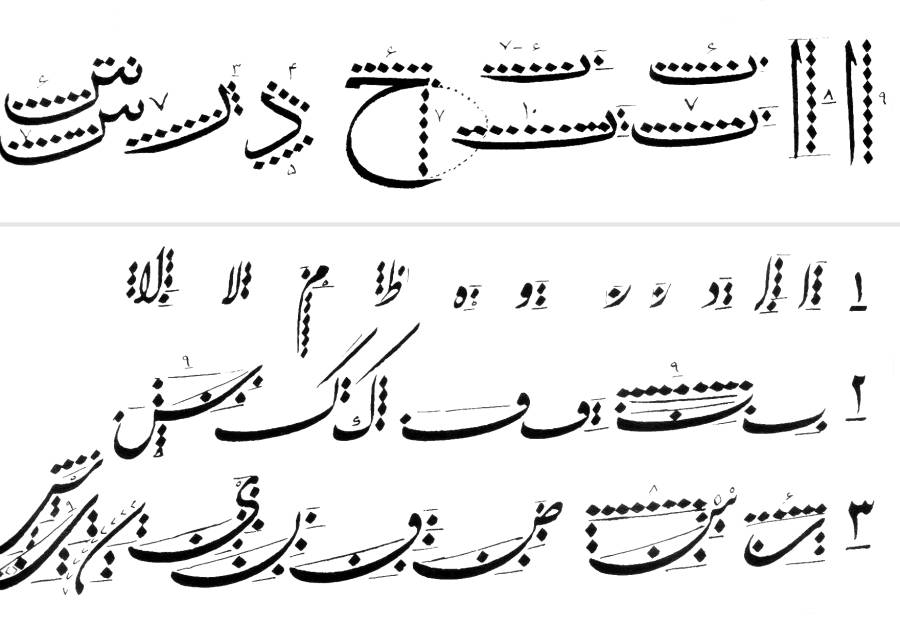
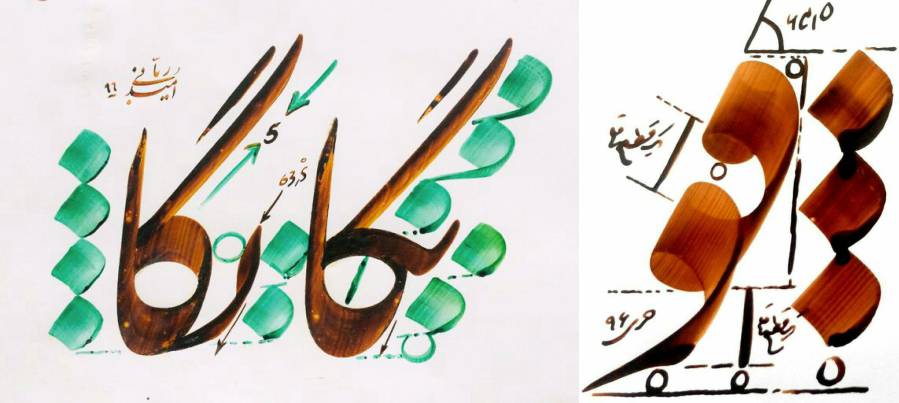
3-خط نستعلیق
خط نستعلیق شناسنامه و نماد هنر ایرانی محسوب شده و به اعتبار تناسب دقیق در دور و سطح آن و نیز به لحاظ جمال شناسی به عروس خطوط اسلامی شهرت دارد. پیوند خط نستعلیق با ادبیات فارسی به گونه ای است که هرگاه واژه ادبیات فارسی شنیده شود، ناخودآگاه تصاویری از خط نستعلیق و آثار ادبی نوشته شده با آن در ذهن متبلور می شود. در طراحی نشانه سایت پرشین لوگوتایپ از نقطه و حرف «واو» خط نستعلیق به صورت مستقیم استفاده شده و حرف «الف» نیز در فرم کلی و خصوصا سرک آن روحیه نستعلیق خود را حفظ کرده است.
4-گل شاه عباسی
استفاده از حرف “واو” نستعلیق و در کنارش حرف “الف” به صورت متعاکس و قرینه، همراه با فرم سر قلم نی، شکل ساده شده ای از گل شاه عباسی را به نمایش گذاشته اند. نقش معروفی که در طرح های فرش، کاشی، تذهیب و دیگر هنرهای اصیل ایرانی بکار رفته و تداعی کننده زیبایی، اصالت و فرهنگ ایرانی است.
5-خط توأمان یا متعاکس
که به نام های مثنی، برگردان و آینه ای(در ترکی) نیز شهرت دارد، از شیوه های تزئینی و تفننی خطاطی بوده است بدین روش که کلمه یا عبارتی را به صورت دوتایی و قرینه هم، در ترکیبی زیبا و چشم نواز، به انواع خطوط کوفی، ثلث، نسخ، نستعلیق، محقق و… می نوشته اند و گاهی هم آن را به هیئت اشکال هندسی، گیاهان و یا سایر موجودات و اشیاء در می آورده اند.
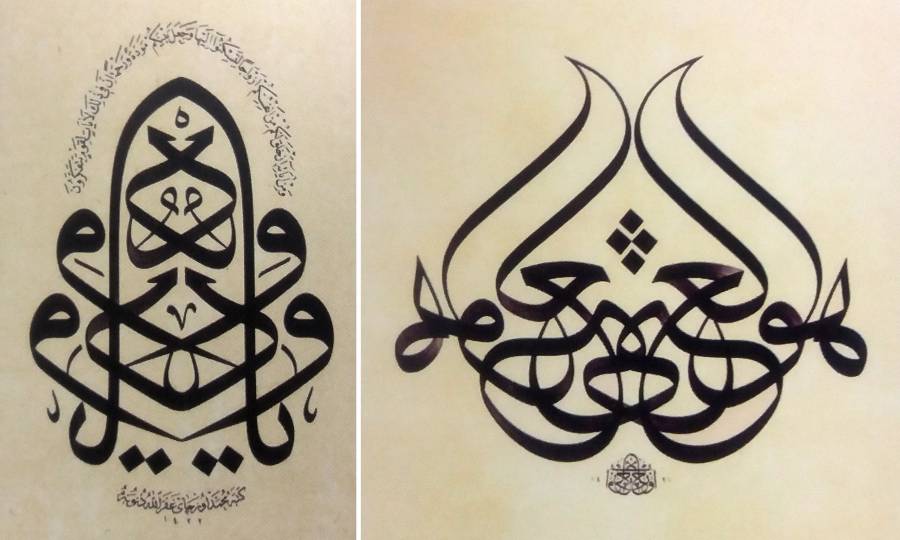
6-حرف “نون” و دلالت های آن
نقطه موجود در دلِ سرِ قلم نی، علاوه بر اینکه تداعی حرف “نون”، اختصار کلمه نشانه نوشته را می کند، به همراه حرف “و” و “الف” قبل خود، دلالت بر آیه یکم سوره مبارکه قلم دارد و جدایی از اینکه اشاره بر عجین بودن خطاطی و خوشنویسی اسلامی با کلام نورانی و الهی دارد، یادآور این مهم است که اگر قلمی حرکت می کند و نقشی می آفریند، همه از فضل و رحمت حضرت باری تعالی است.
ن وَالْقَلَمِ وَمَا يَسْطُرُونَ (ن و قسم به قلم و آن چه خواهند نگاشت.)
نون از حروف مقطعه قرآن است که طبق آنچه در تفاسیر آمده، حروف مقطعه نشانه های اختصاری یا رمزهایی از نام ها و صفات الهی هستند.
علامه طباطبایی در تفسیر المیزان جلد 19 صفحه 630 می آورد:
… اصبغ بن نباته از امیرالمؤمنین (علیه السلام) روایت کرده که در تفسیر آیه «ن و القلم و ما یسطرون» فرمود: منظور از قلم، قلمى است از نور و کتابى از نور که در لوح محفوظ قرار دارد و مقربین درگاه خدا شاهد آنند…
در تفسیر نور نیز آمده است:
سوگند به قلم، نشانه فرهنگ و تمدن است، تکیه بر قلم تکیه بر سند و استدلال است. قلم تجربه قرن ها را به هم منتقل می کند و فرهنگ ها را رشد می دهد. افراد را با قلم می توان خواب یا بیدار کرد…
7- نور و شعله آتش
در فضای بیاض یا سفید (یا در اصطلاح گرافیک فضای منفی) داخل سر قلم نی، شعله شمعی نمایان است که با توجه به تفسیر آیه «ن و القلم و ما یسطرون» و جنس نور بودن قلم، با آن قرابت معنایی دارد. همچنین فرم کلی نشانه علاوه بر اینکه تداعی گل اسلیمی می کند به فرم شعله آتش نیز شباهت دارد که همانطور که در توضیحات قلم نی اشاره شد، شعله نیز مفهوم و معنایی پرکاربرد در ادبیات کهن پارسی دارد و با “نی” تجانس معنایی دارد مانند آنجایی که جلال الدین محمد بلخی می سراید: آتش است این بانگ نای و نیست باد… هر که این آتش ندارد نیست باد…
رنگ های بکار رفته در طراحی نشانه سایت پرشین لوگوتایپ
قرمز ایرانی (Persian Red)
رنگی که تحت عنوان Persian Red یا قرمز ایرانی در سال 1897 میلادی به ثبت رسیده است، رنگ نارنجی متمایل به قرمزی همرنگ خاک و دانه های رنگی موجود در خلیج فارس و خاک سرخ جزیره های آن است که از ترکیبات سیلیکات آهن و آلومینیوم همراه با منگنز ساخته شده اند. این رنگ با رنگ قلم نی مرغوب برای خوشنویسی نیز شباهت دارد. ضمن اینکه رنگ قرمز از رنگهای پر استفاده درفرشهای ایرانیست که از گیاهی به نام روناس استخراج می شود.